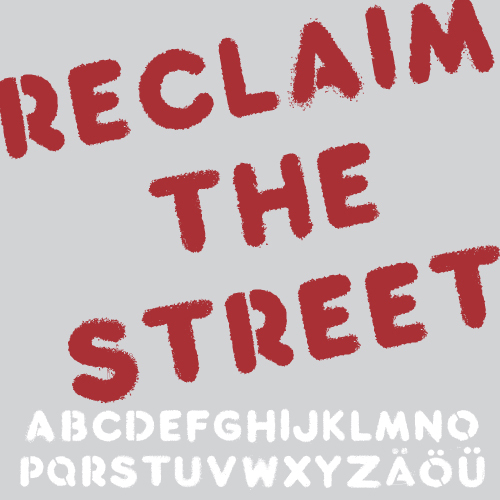
Reclaim autorstwa Nilsa von Blanca to darmowy krój displayowy z efektem erozji, o surowym, ręcznie ciosanym charakterze. Litery wyglądają na ciężkie i zniszczone, z rozmytymi krawędziami i wytartymi rogami, przez co sprawiają wrażenie pieczątek, a nie rysunków, co nadaje całemu krojowi szorstki, odzyskany klimat.
Pasuje do plakatów, okładek płyt, grafik skate’owych i streetwearowych, ulotek protestacyjnych oraz tytułów, gdzie surowa tekstura ma za zadanie mówić sama za siebie. Jako darmowy font, Reclaim sprawdza się również w krótkich nagłówkach, hasłach na okładki i wyrazistych monogramach, ponieważ masywne kształty pozostają czytelne, a zniekształcony obrys dodaje im dynamiki.
Reclaim to krój pisma stworzony przez Nilsa von Blanca.